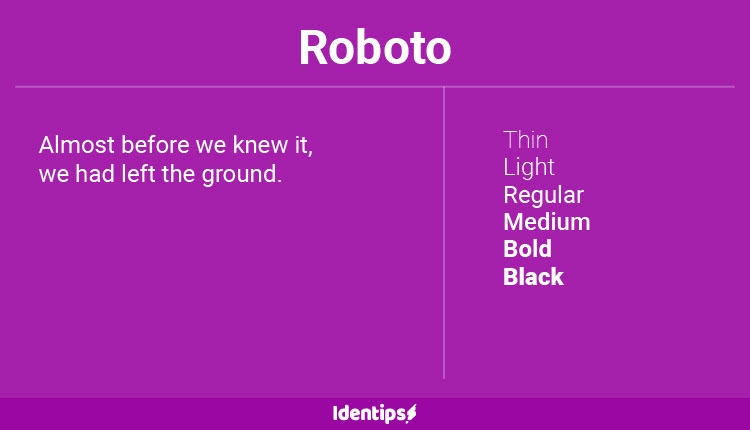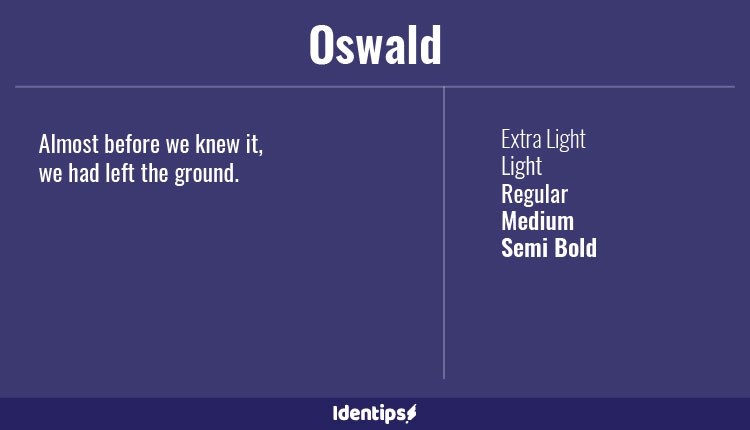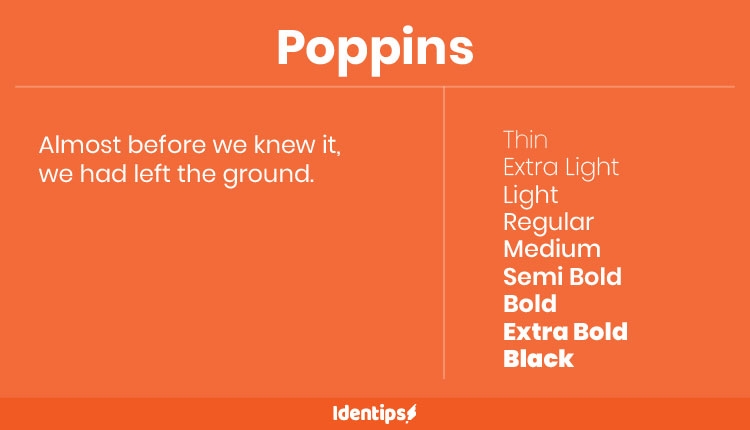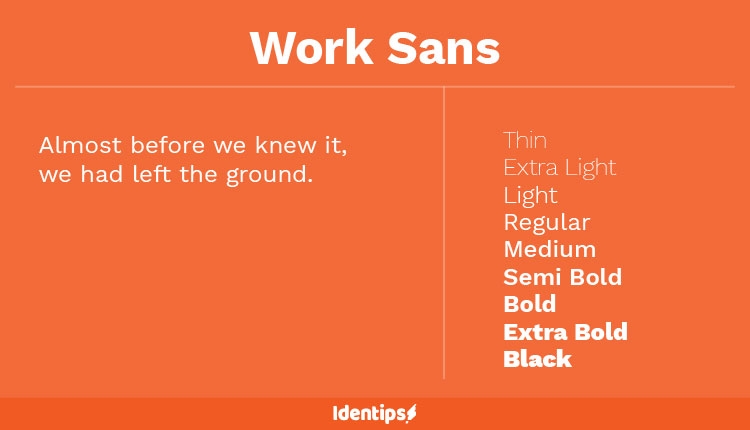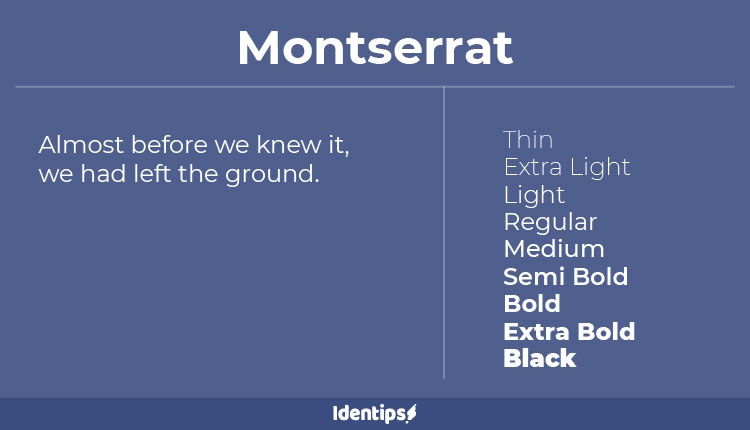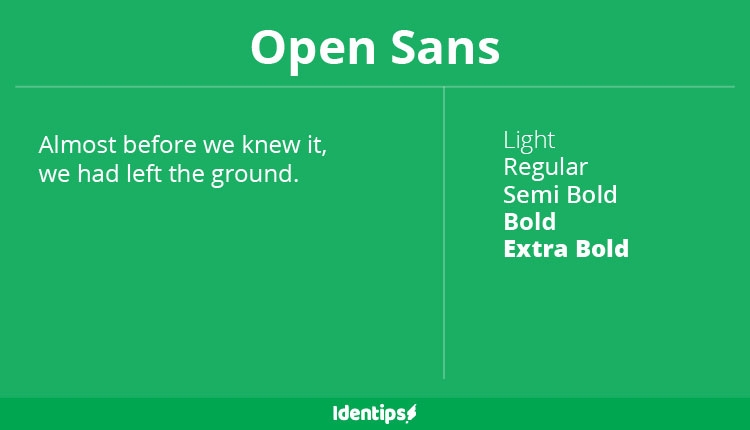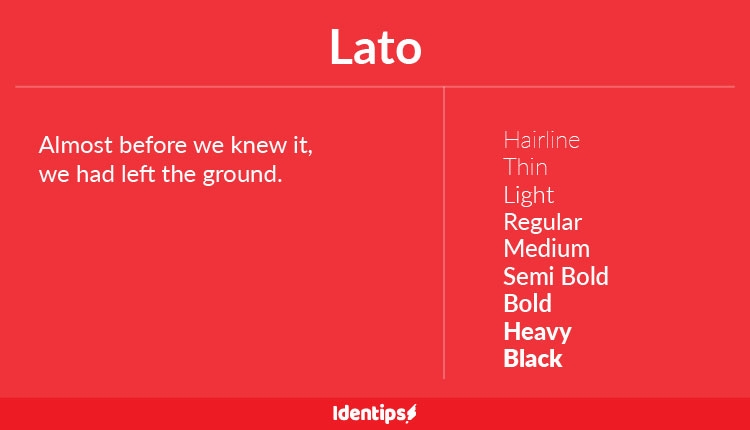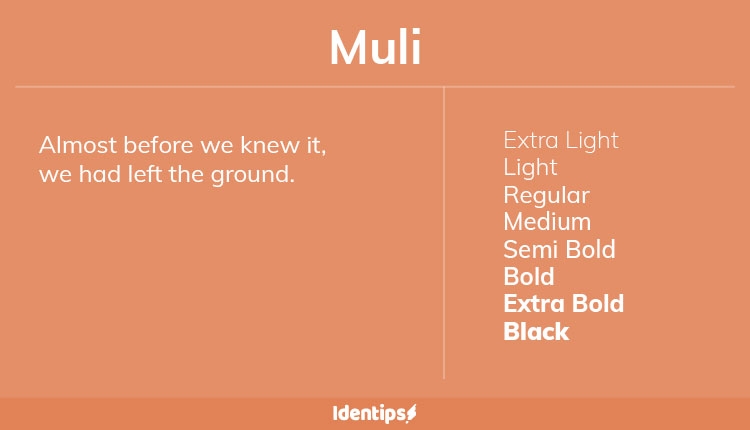
10 Rekomendasi Font Terbaik Untuk Website
Halo, selamat datang di Identips! Pada artikel kali ini saya akan membahas beberapa rekomendasi font terbaik untuk website kamu. Saat ini sudah banyak penyedia webfont gratis yang meneydiakan cukup banyak jenis font yang dapat kamu gunakan pada website kamu, contohnya adalah Google Fonts dari Google dan Typekit dari Adobe. Pemilihan font atau tipografi dalam sebuah website akan mempengaruhi tampilan website serta pengalaman pengguna dari website tersebut, jadi kamu harus berhati-hati dalam memilih font. Pada artikel yang lain saya sudah pernah menulis tips tipografi untuk desain interface. Berikut ini adalah beberapa rekomendasi font gratis dari Identips yang dapat kamu gunakan untuk website kamu:
Montserrat
Font yang dikembangkan oleh Julieta Ulanovsky pada tahun 2010 ini merupakan font terbaik untuk website. Font ini diluncurkan sebagai project Kickstarter pada tahun 2011, kemudian dirilis untuk publik melalui Google Fonts.
Lato
Font terbaik untuk website yang selanjutnya adalah Lato. Lato merupakan sebuah font yang dirancang oleh Warsawukasz Dziedzic, seorang desainer yang berbasis di Warsawa pada tahun 2010. Dalam bahasa Polandia, "Lato" berarti "Musim panas". Font ini diterbitkan pada Desember 2010 dibawah Open Font License oleh pendiri tyPoland dengan dukungan dari Google.
Merriweather
Merriweather dirancang dengan dengan model huruf yang sangat optimal untuk dibaca pada layar. X-height dari font ini lumayan besar sehingga membuat tingkat keterbacaan font ini semakin baik sehigga Merriweather dapat dikategorikan sebagai font terbaik untuk website. Menurut saya font ini cocok digunakan untuk tajuk judul dan juga paragraf.
Muli
Muli juga merupakan salah satu font terbaik untuk website. Font Sans Serif minimalis ini dirancang oleh Vernon Adams. Muli sangat cocok digunakan untuk tampilan layar maupun tipografi untuk paragraf, karena jarak antar karakter yang pas membuat tingkat keterbacaannya cukup baik.
Nunito
Font terbaik untuk website selanjutnya adalah Nunito. Sama seperti Muli, Nunito juga dirancang oleh Vernon Adams untuk tampilan layar. Nunito memiliki berbagai macam tingkat ketebalan sehingga membuat font ini menjadi sebaguna dan menarik untuk digunakan.
Oswald
Osswald merupakan sebuah pengerjaan ulang dari font Alternate Gothic pada awal abad kedua puluh. Font Oswald dirancang oleh Vernon Adams untuk digunakan pada perangkat digital seperti komputer dan perangkat seluler. Font Oswald ini cocok jika ditempatkan pada tajuk judul website kamu.
Poppins
Poppins adalah font sans-serif geometris yang dirancang oleh Indian Type Foundry. Font ini mendukung lebih dari 150 bahasa termasuk bahasa Hindi dan Sanskerta.
Roboto
Roboto merupakan salah satu font yang paling banyak diunduh di situs Google Fonts. Tampilannya yang sederhana dan memiliki kesan yang profesional membuat font ini diminati banyak orang. Roboto ini banyak digunakan pada beberapa produk Google, seperti Android dan Chrome OS.
Work Sans
Work Sans dirancang oleh Wei Huang. Work Sans dirancang berdasarkan grotesques (inspirasi untuk semua font sans-serif) dari pergantian abad kedua puluh. Bobot font yang berbeda dirancang untuk penggunaan yang berbeda, bobot reguler dan medium ditujukan untuk penggunaan teks, sedangkan bobot yang lebih berat dan lebih ringan dioptimalkan untuk dispalay. Work Sans dirancang oleh Wei Huang. Work Sans dirancang berdasarkan grotesques (inspirasi untuk semua font sans-serif) dari pergantian abad kedua puluh. Bobot font yang berbeda dirancang untuk penggunaan yang berbeda, bobot reguler dan medium ditujukan untuk penggunaan teks, sedangkan bobot yang lebih berat dan lebih ringan dioptimalkan untuk dispalay.
Open Sans
Font ini dirancang oleh Steve Matteso, dan merupakan salah satu font yang sangat pupuler. Bentuknya yang sederhana membuat font ini cocok jika disandingkan dengan berbagai jenis font sehingga membuat font ini menjadi salah satu font terbaik untuk website.
Itulah diatas beberapa rekomendasi font terbaik untuk website, jika kamu memiliki rekomendasi font yang lain, silahkan tuliskan pada kolom komentar.